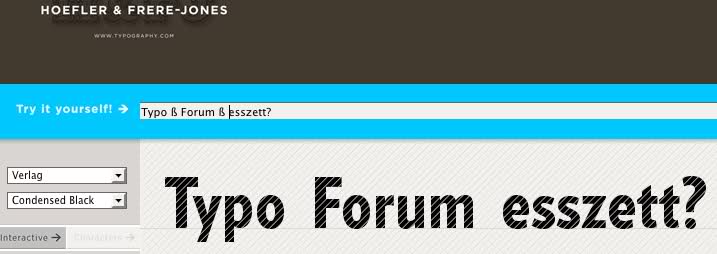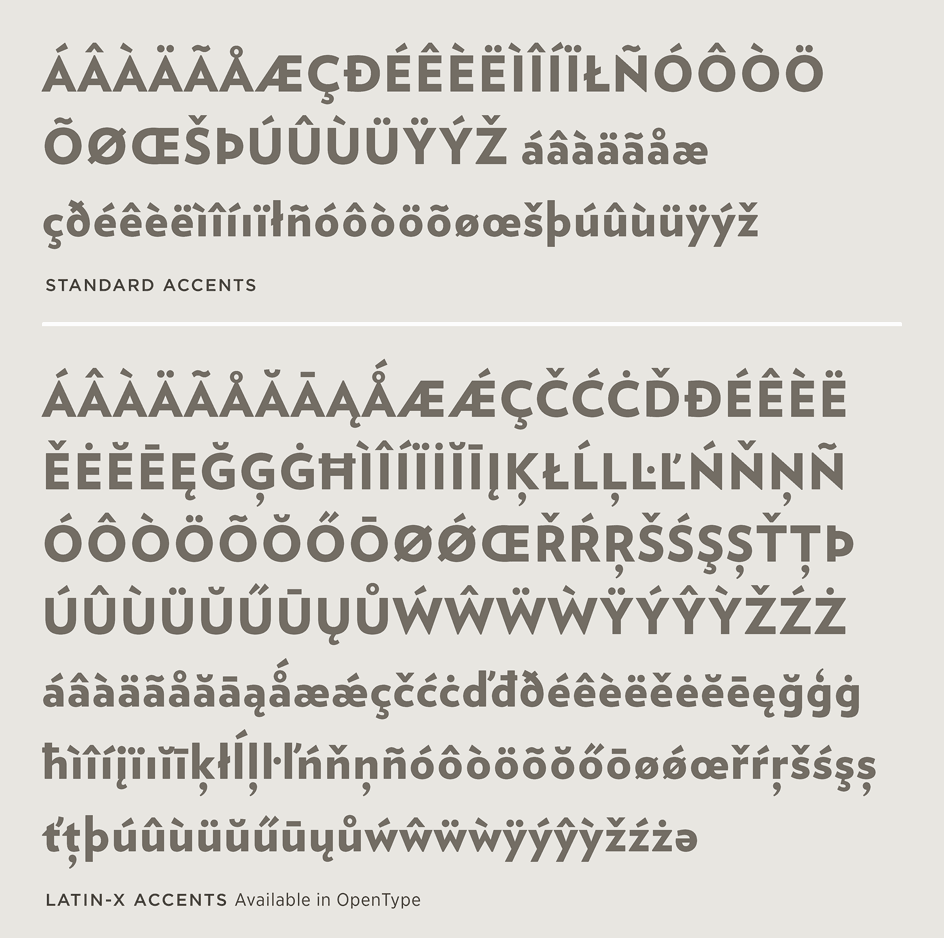
Alternativen zu VERLAG
ich suche nach einer oder auch gern mehrerer alternativer Vorschläge zur VERLAG von Hoefler Type.
Sie hat mir für meinen Bedarf einfach etwas zu fette Versalien im Bezug zu den Gemeinen. Von der Anmutung ist sie allerdings genau das, was ich suchen würde.
Tja, meine Augen sind noch ziemlich gut: fettere versalien?- absolut nicht, und was du an diesen superclone so toll findest kann ich eh nicht nachvollziehen - eine zeitgeistschrift eben. vergleiche bitte mal mit eine reihe von sans klassiker (vorbilder). und was ist mit dem ß ? brauchst du nicht? bei hoefler fehlt der im angebot. ist es in wien auch so "heiß".... :roll:
Die Verlag hat sehr wohl ein ß:
Die Erbar Grotesk von URWPP scheint in die Richtung zu gehen, aber es gibt wesentlich weniger Schnitte (keine Condensed und Compressed): :cheer:
Vielleicht wäre die Avenir auch eine mögliche Alternative? :?
Mal was zum Spielen aber garantiert nicht profitauglich: http://uwes.suche-plus.de/galerie5b.html und http://uwes.suche-plus.de/galerie5c.html Auslöser waren Gewürzglasettiketten und Lieferscheine im Retrodesign als reines Spaßprojekt garantiert ohne Zukunft und Futur(a).
aber was für eins!
Über die Form lässt sich wahrlich streiten. Ich wollte nur darauf hinweisen, dass in der Verlag ein ß enthalten ist. Ich finde es nicht gut, wenn – wie hier von TypoLion – einfach was behauptet wird, was so nicht stimmt.
ja, deine antwort war unbestritten hilfreich. es erstaunt mich nur, dass h&fj die glyphe nicht mal in der (den anschein von vollständig erweckenden) sonderzeichenübersicht zeigen.
im test driver haben sie das ›ß‹ bei den ligaturen versteckt, wo es – historisch gesehen – ja hingehören mag, aber doch relativ schwer zu ?nden ist. heute morgen habe ich es dort jedenfalls nicht entdeckt, sondern erst jetzt, da ich durch dich weiß, wie es aussieht.
Ich weiß nicht, was ihr habt. Das scharfe s ist doch hübsch und folgt einem alten Vorbild. Okay, es ist jetzt nicht unbedingt zukunftsorientiert, aber … hübsch.
Diese ß ist einfach nur das sz aus der Fraktur in Grotesk umgesetzt. Das war in den statischen Grotesk der 1920ern noch üblich. Ich kann mich der Kritik daran auch nicht anschließen. Außerdem sieht es geiler aus als das blöde Titten-Scharf-S.
liebe typomanen- das muß (ein esszett auf mein keyboard - mac os x 10.4.11 - G4) ich richtig stellen - siehe testdrive von hoefler. und wenn ich uwe richtig verstehe sollte "maßstab" so geschrieben werden, wie in den roaring twenties? ist nicht dein ernst, oder- aber da ging's unser catsspell auch gar nicht drum, oder
Beachte den Satz: »Some characters may not be accessible from your keyboard«. Viele der Online-Testtools verweigern die Anzeige internationaler Glyphen. Ist ein Problem der Tools und nicht der Schrift.
Und das ß mag klassisch aussehen, manchen gefällt's aber und in dem einen oder anderen Projekt kann es auch sinnvoll sein. Interessant finde ich, dass es keine OpenType-Alternative dazu gibt, die mehr dem Heute zugewandt wäre. Andere Schriften haben ja z. B. eine Unmenge an Ampersand-Varianten. Oder gibt’s eine ß-Variante auch in der Verlag?